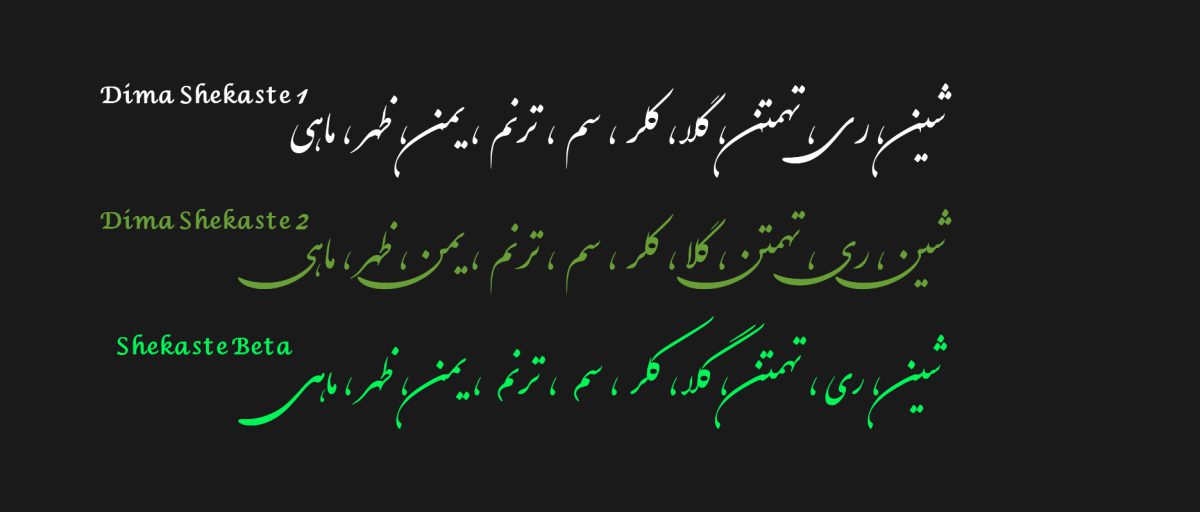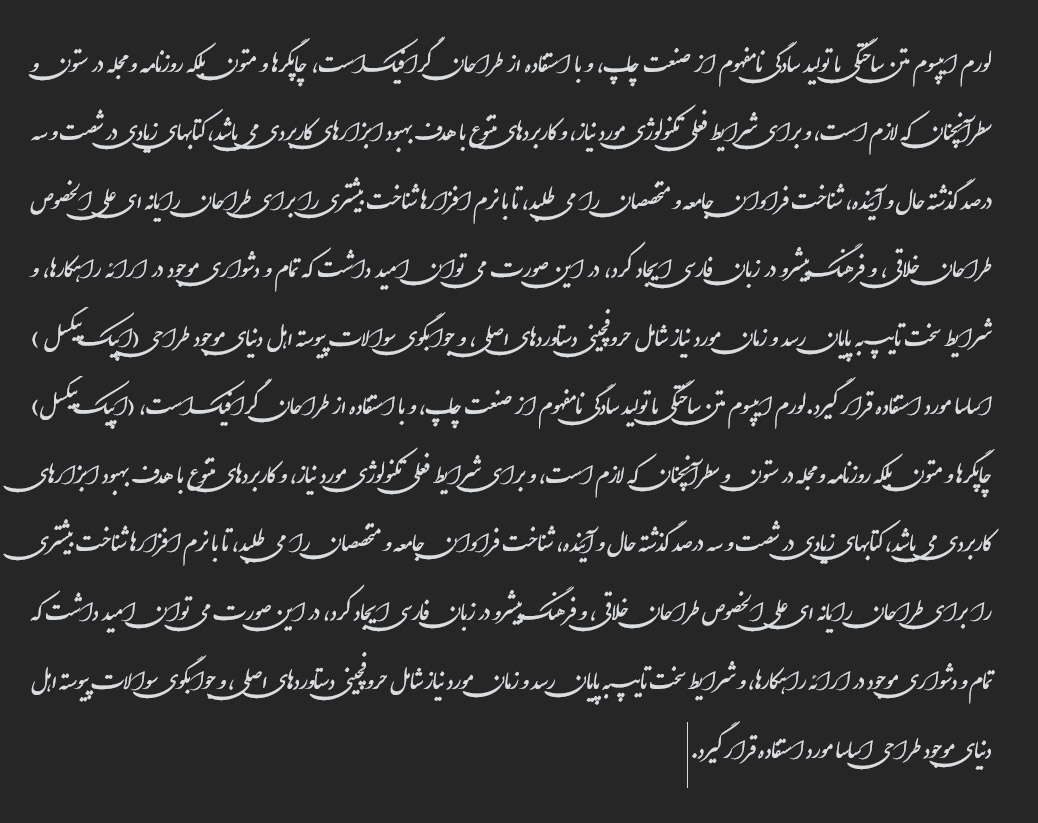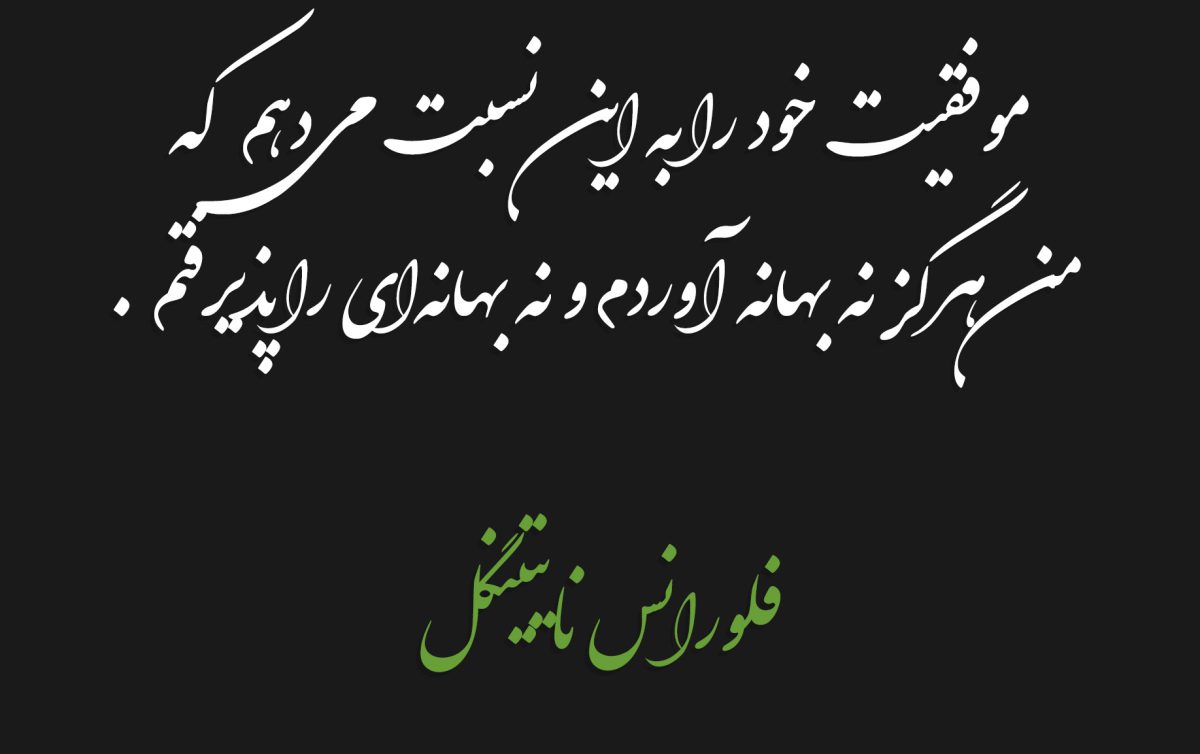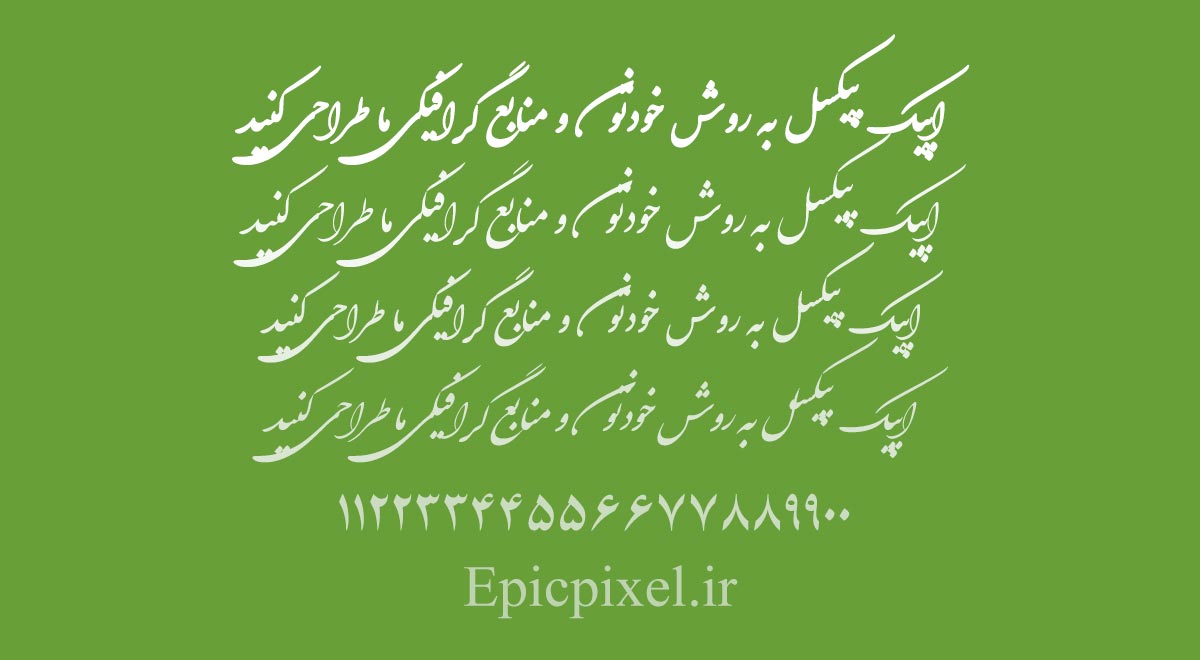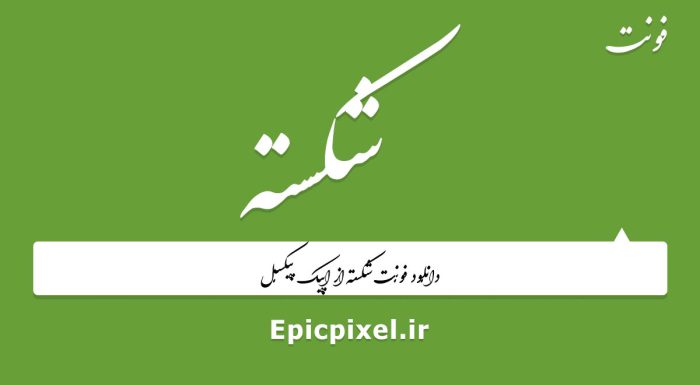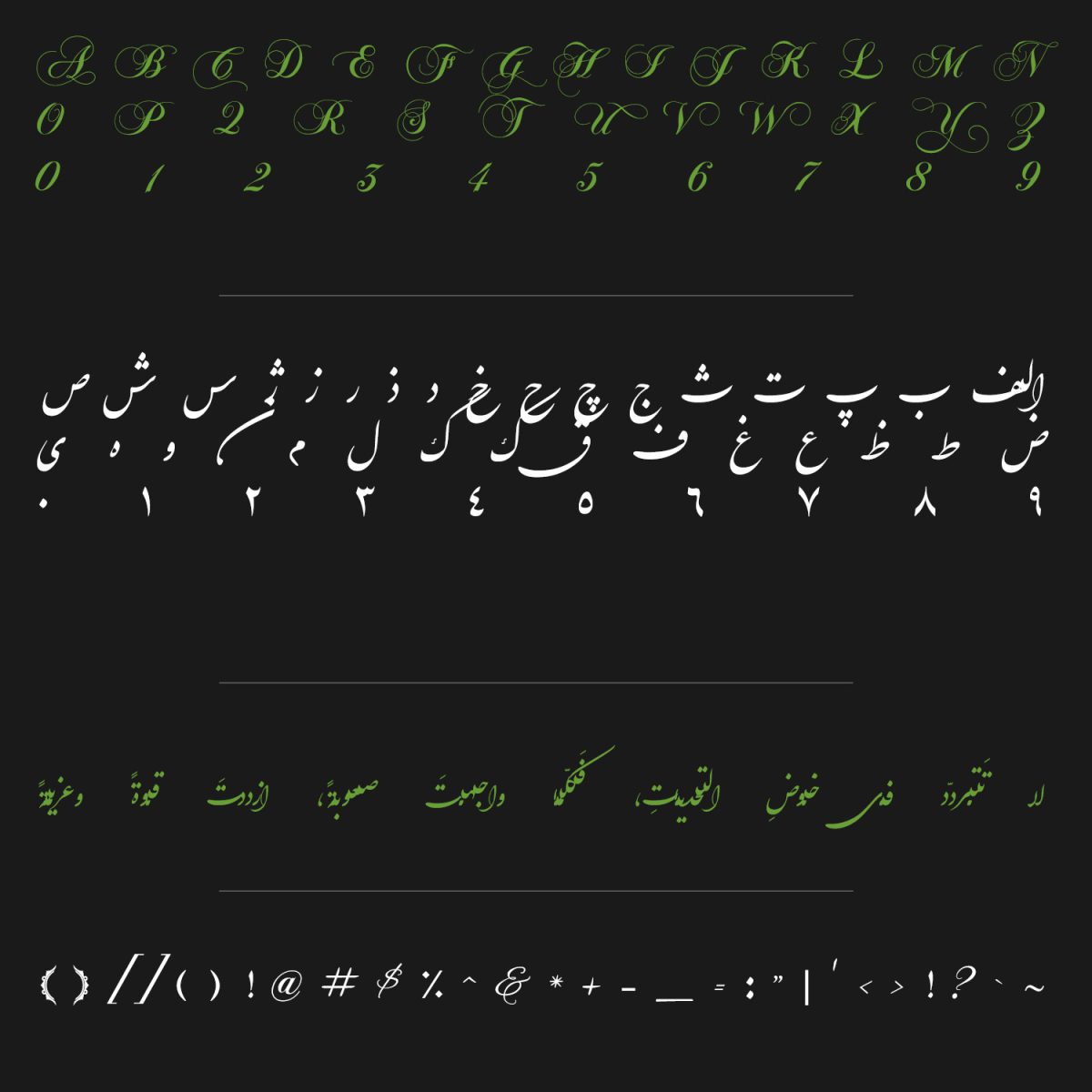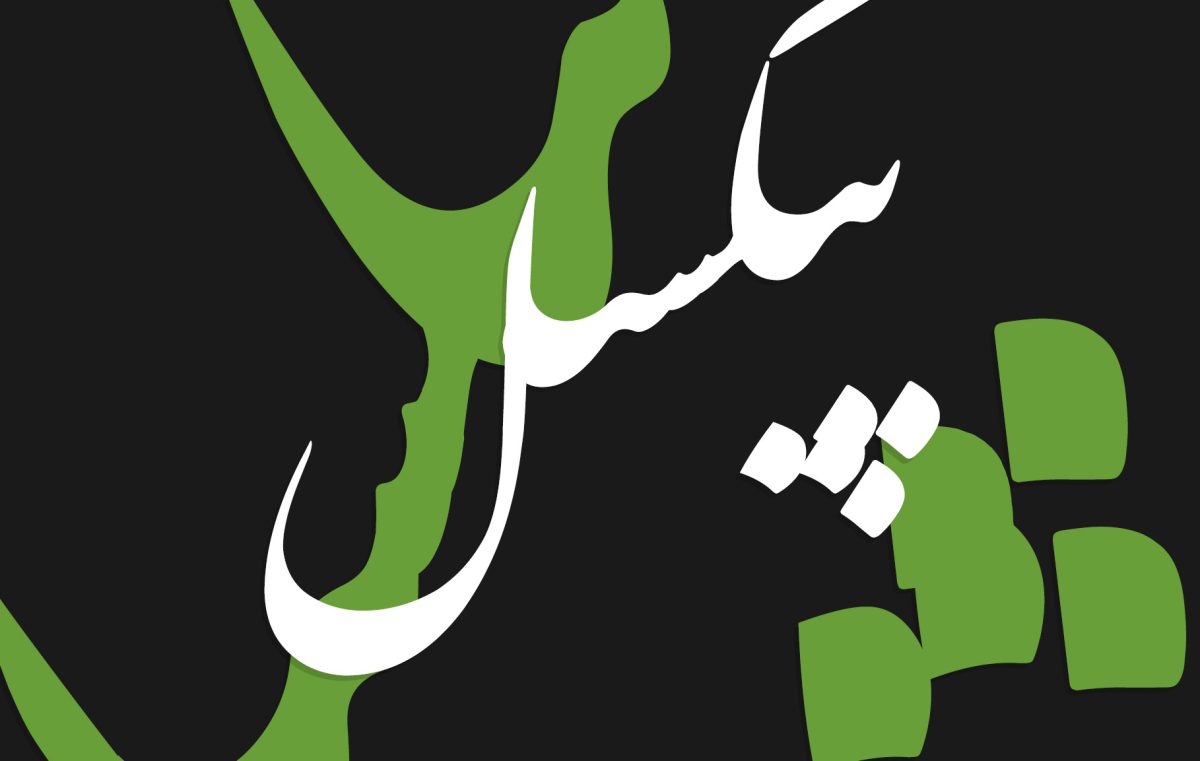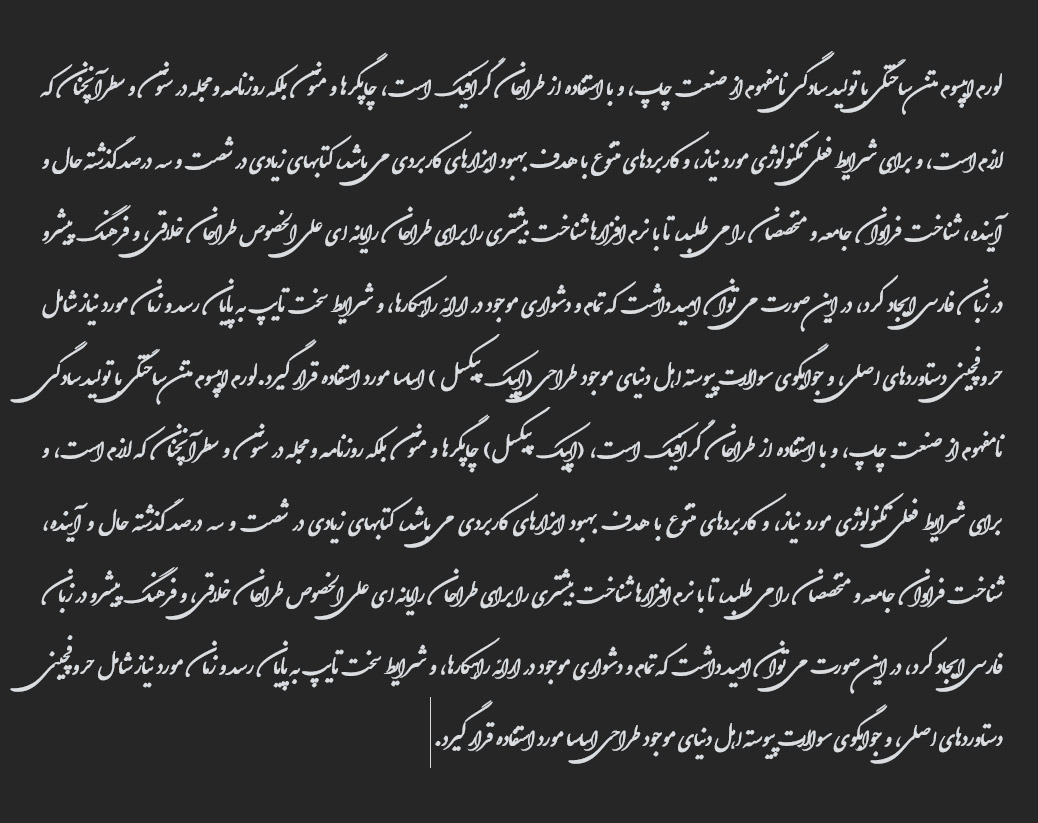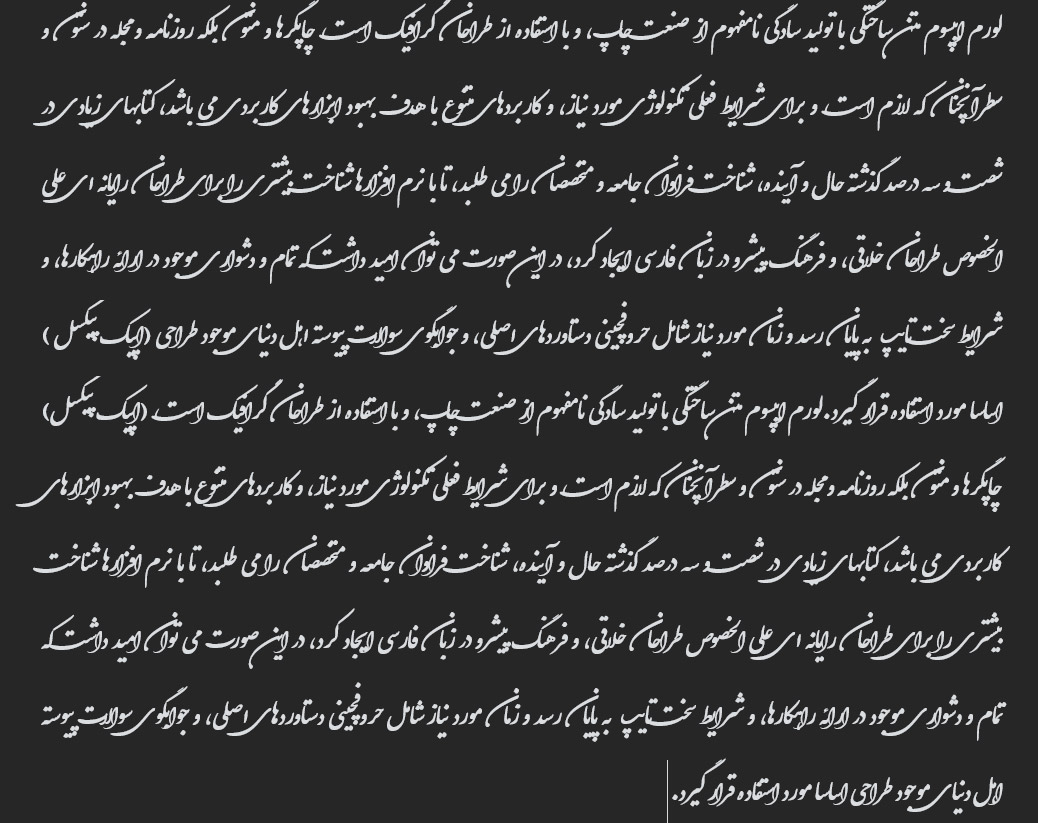
4 فونت شکسته فارسی Shekasteh
فونت نستعلیق شکسته (Shekasteh)، سبک متمایزی از فونت های خوشنویسی ایرانی برپایه خط نستعلیق است که با خطوط هنری و ظرافت های ویژه خود، جلوه ای اصیل و زیبا به طرح ها می بخشد. نسخه های متنوعی از این فونت، از جمله Shekasteh Beta, (در 2نسخه) Dima Shekasteh (در 2 نسخه), Shekasteh Beta و Iran Nastaliq Shekasteh، با ویژگی های منحصربه فرد (مانند تایپ مستقیم، کشیده نویسی، رفع مشکلات اتصال) در فرمت های TTF و OTF ارائه شده اند. این مجموعه فونت به طور گسترده برای دانلود بوده و مناسب طراحی های گرافیکی و چاپ، لوگوتایپ، تایپوگرافی و متون نمایشی است و با وجود ظاهر هنری، خوانایی بالایی نیز دارد. فونت های شکسته نستعلیف بصورت جداگونه رایگان میتونید از سراسر نت پیدا کنید .
مجموعه فونت های شکسته نستعلیق: زیبایی خطاطی ایرانی برای طراحی دیجیتال و چاپی
فونت نستعلیق شکسته (Shekasteh)، یکی از زیباترین و خاص ترین سبک های فونت فارسی محسوب می شود که به خانواده نستعلیق تعلق دارد اما با خطوط هنری و ظرافت های ویژه و حروف شکسته متفاوت وزیبا، طراحی ها و تایپوگرافی های فارسی را به سطحی متفاوت ارتقا می دهد. این فونت الهام گرفته از هنر اصیل خطاطی نستعلیق ایرانی است و با استفاده از تکنیک های حرفه ای خطاطی دیجیتال ایجاد شده است. جزئیات دقیق و خطوط منحنی زیبا در این قلم، حس و حال هنر اصیل ایرانی را به هر متن و طرحی می بخشد و جلوه ای شکسته و پر پیچ و خم دارد که آن را برای کارهای هنری و نمایشی ایده آل می کند. اگر به دنبال فونتی هستید که اصالت و هنر خطاطی ایرانی را در قالبی دیجیتال به نمایش بگذارد، این فونت گزینه ای بی نظیر خواهد بود. این فونت در برخی منابع به عنوان حرفه ای ترین فونت نستعلیق نامیده شده است.
دانلودنسخه ها و پیاده سازی های متنوعی از فونت نستعلیق شکسته در دسترس قرار دارد که هر یک ویژگی های خاص خود را دارند. از جمله آن ها می توان به فونت نستعلیق شکسته پرو اشاره کرد که با دارا بودن جزئیات دقیق، حفظ خوانایی بالا برای متن های بلند و کوتاه و سازگاری با انواع نرم افزارهای گرافیکی معرفی شده است. فونت دیما شکسته (Dima Shekasteh) یکی دیگر از فونت های خانواده نستعلیق است که توسط آقای روح الله بلوردی طراحی شده و در سه نسخه ارائه شده است: نسخه ۱ با تعداد محدودی کاراکتر خط شکسته، نسخه ۲ با تعداد ترکیب های شکسته بیشتر برای نزدیکی به خط شکسته کامل تر، و نسخه ۳ که در آن از برخی حروف رسم الخط آقای سید محمد زاهدی برای زیبایی بیشتر استفاده شده است. این نسخه ها بر روی همدیگر بازنویسی نمی شوند و می توانید آن ها را در کنار یکدیگر استفاده کنید. نسخه فونت شکسته (بتا) نیز توسط آقای علی سواری در سال ۱۳۹۱ ساخته شده است. فونت نستعلیق شکسته ایران نسخه دیگری است که توسط تیم طراحی ویژوال فایل ویرایش شده و به طور خاص برای رفع مشکل جدانویسی و مشکلات در اتصال کلمات ارائه می شود و دارای قابلیت تایپ مستقیم (بدون نیاز به نرم افزارهای جانبی خوشنویسی) و قابلیت کشیده نویسی حروف بدون مشکل و تغییر شکل حروف با کلید های ترکیبی (با پشتیبانی OpenType) است. این فونت متفاوت با سایر فونت های نستعلیق موجود نامیده شده است.
با وجود ظرافت های زیاد و سبک شکسته، خط شکسته نستعلیق همچنان دارای خوانایی مناسبی است که آن را برای متن های بلند و کوتاه مناسب می سازد، هرچند کاربرد اصلی آن معمولاً در عناوین و متون نمایشی است که زیبایی آن بیشتر به چشم می آید.
کاربردهای فونت نستعلیق شکسته در طراحی گرافیک و وب
با توجه به طراحی خاص و منحصر به فرد، خطوط هنری و ظرافت های ویژه، و حفظ خوانایی بالا، فونت نستعلیق شکسته کاربردهای گسترده ای در طراحی گرافیک و وب دارد. این قلم برای پروژه های طراحی گرافیکی و دیجیتال، پوسترها، بروشورها، و محتوای شبکه های اجتماعی بسیار مناسب است و جلوه ای هنری و سنتی به آن ها می بخشد. همچنین برای تایپوگرافی فارسی، پروژه های تبلیغاتی، کارت های دعوت، طراحی های هنری، و محتوای وب فارسی کاربرد دارد. این فونت مناسب تایپوگرافی، عنوان نویسی، لوگو تایپ، و بنر نویسی است و برای خوشنویسی دیجیتال نیز استفاده می شود. قابلیت استفاده در نرم افزارهای گرافیکی مختلف و تایپ مستقیم آن را به ابزاری همه کاره برای ساخت عکس نوشته های گرافیکی و ایجاد طرح های تایپوگرافی (چیدمان حروف) و نیز برای لوگو تایپ، پوستر و تمامی طرح های گرافیکی تبدیل کرده است.
مجموعه کامل فونت Shekasteh فارسی